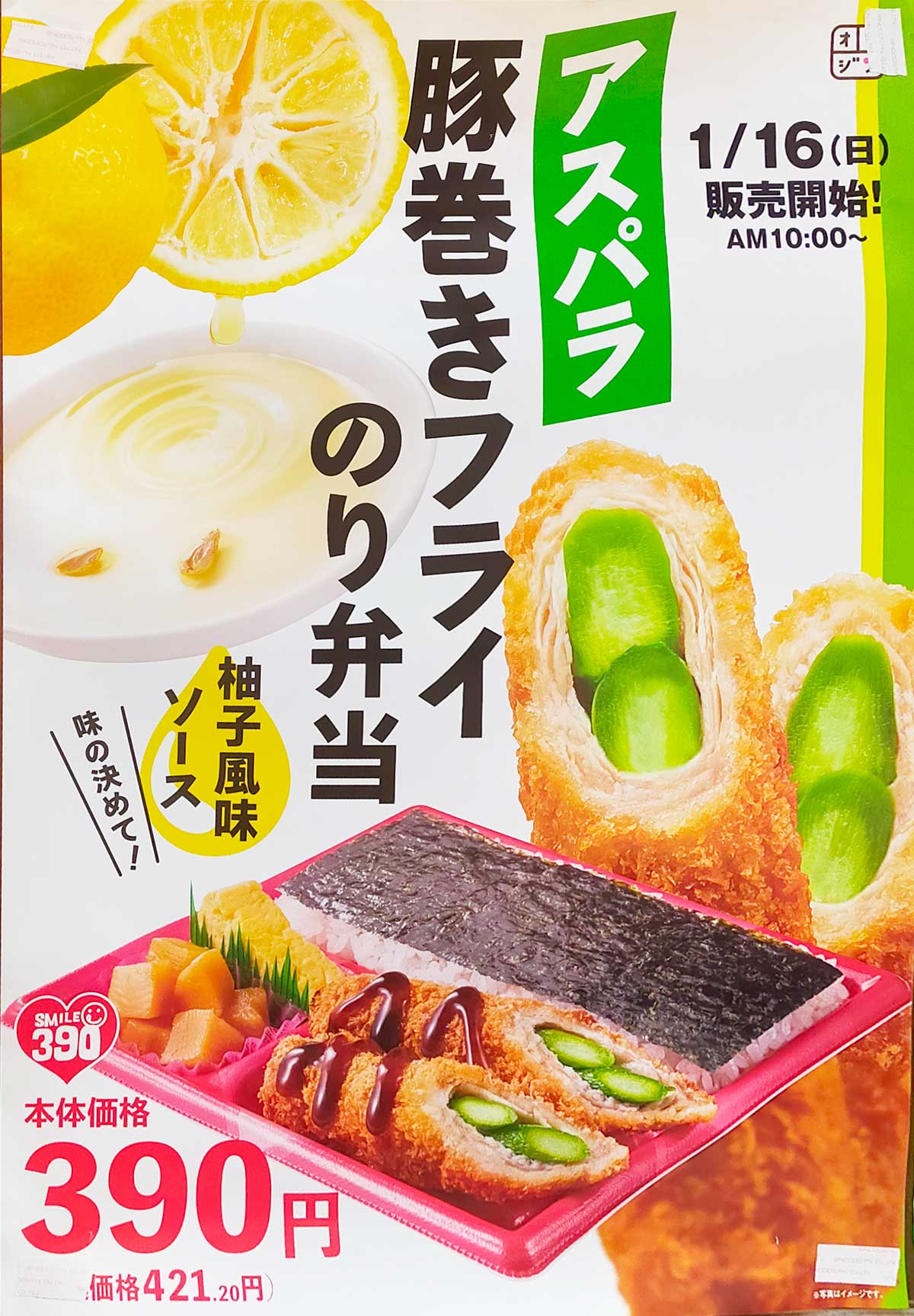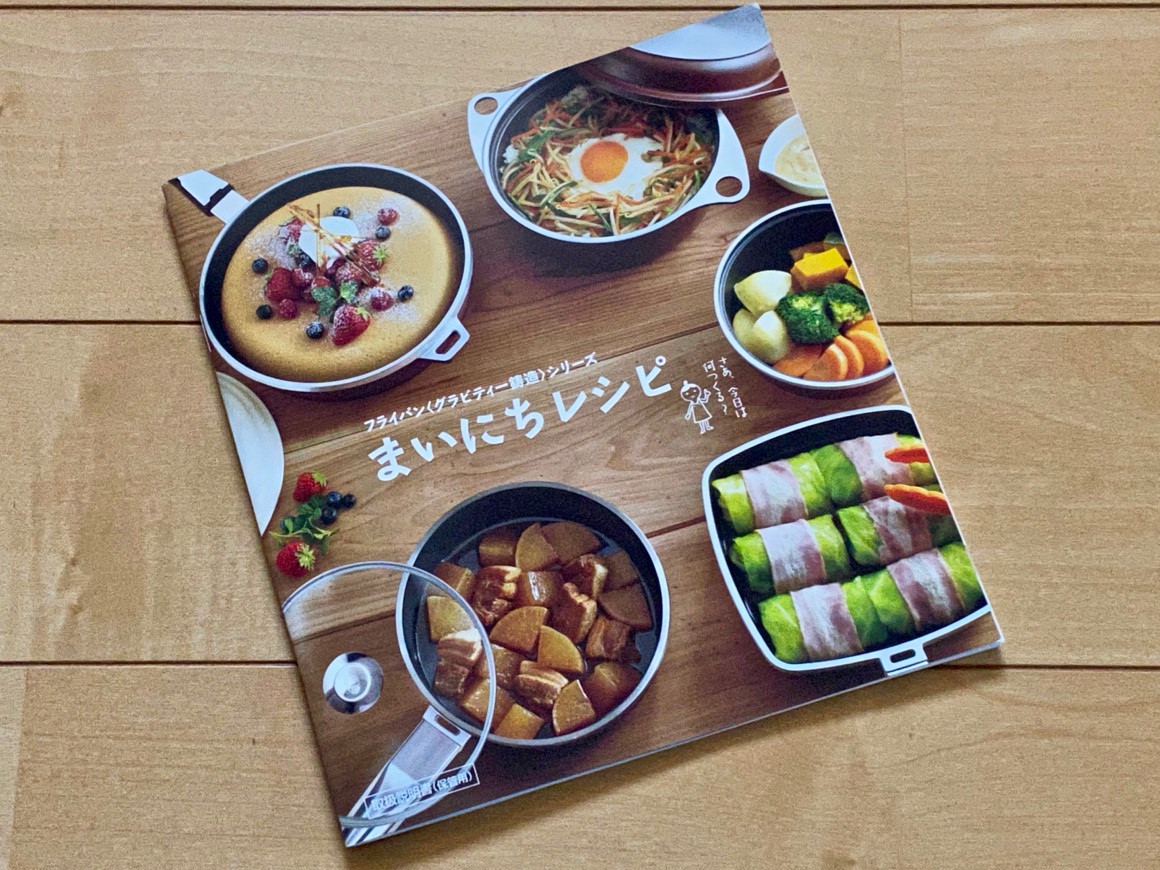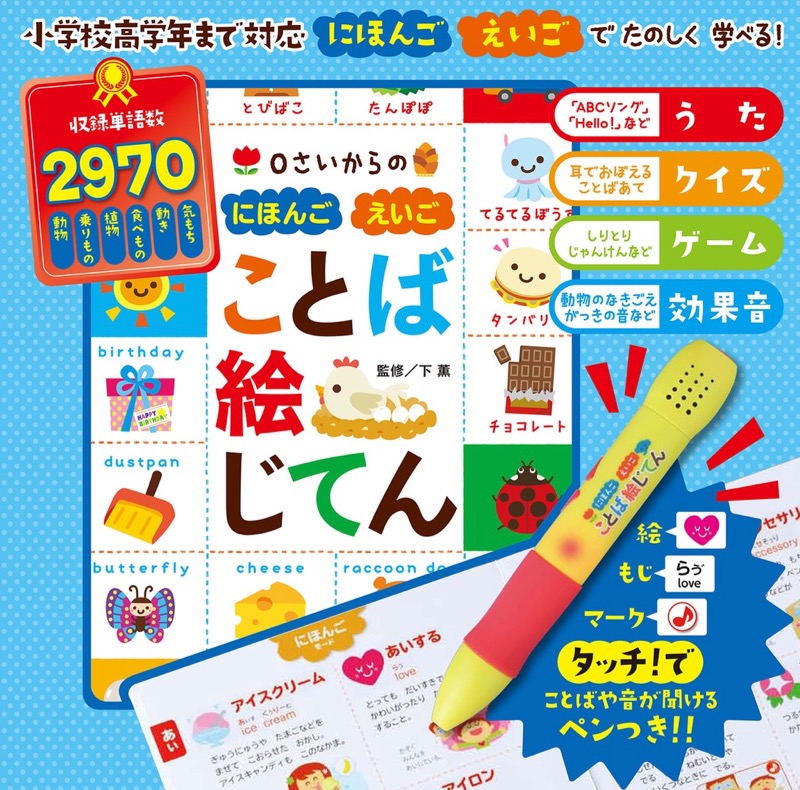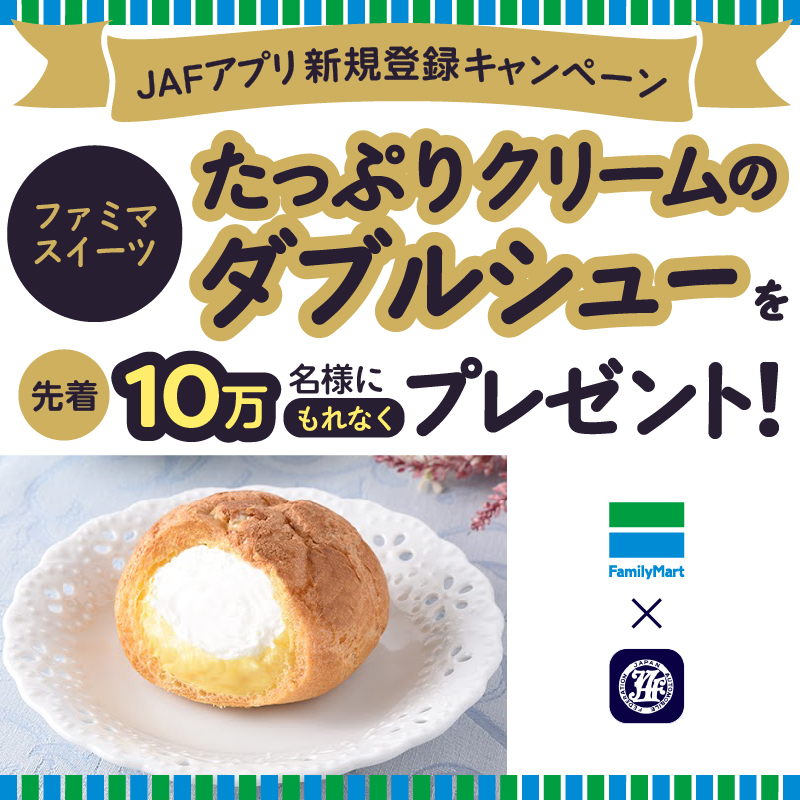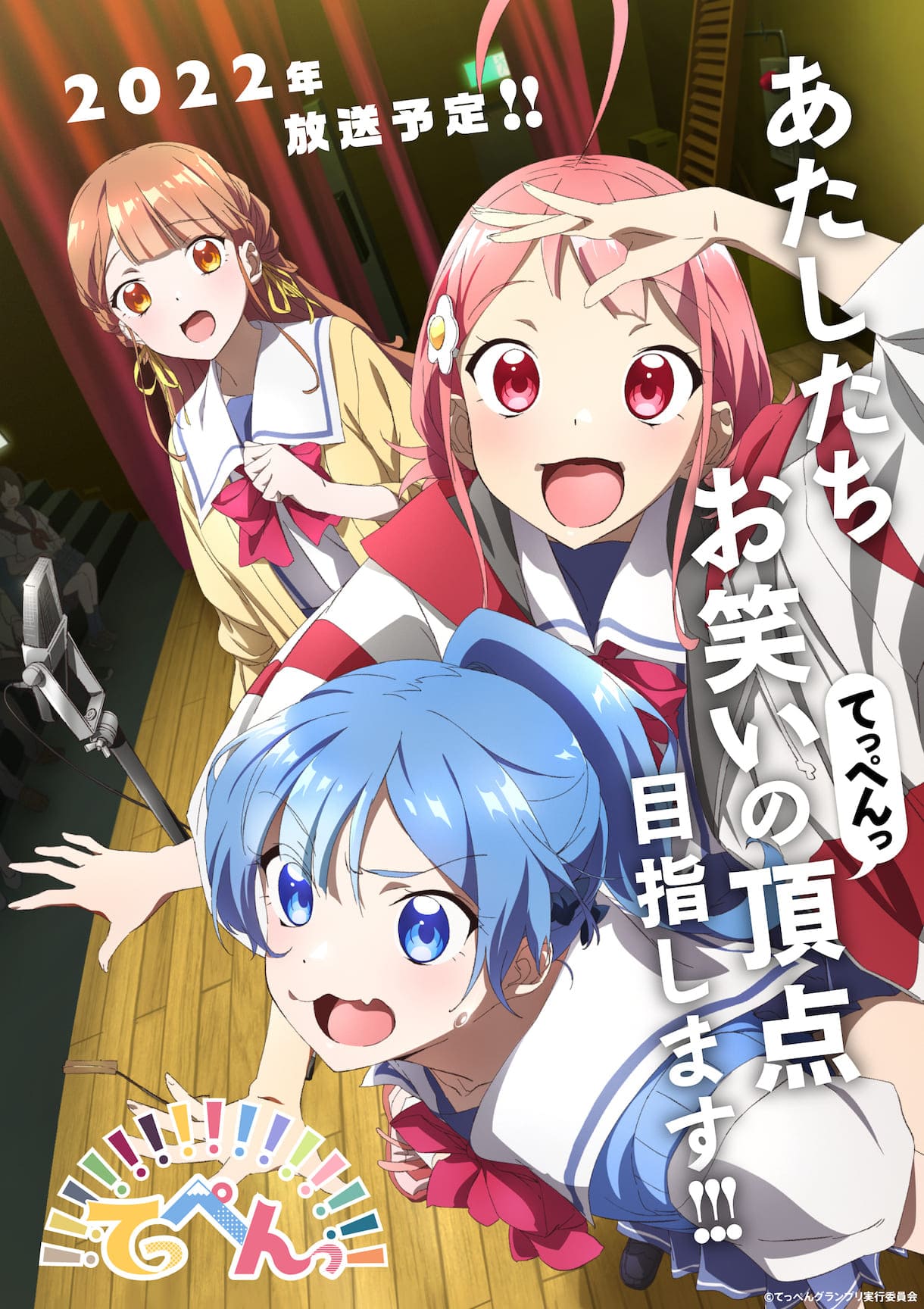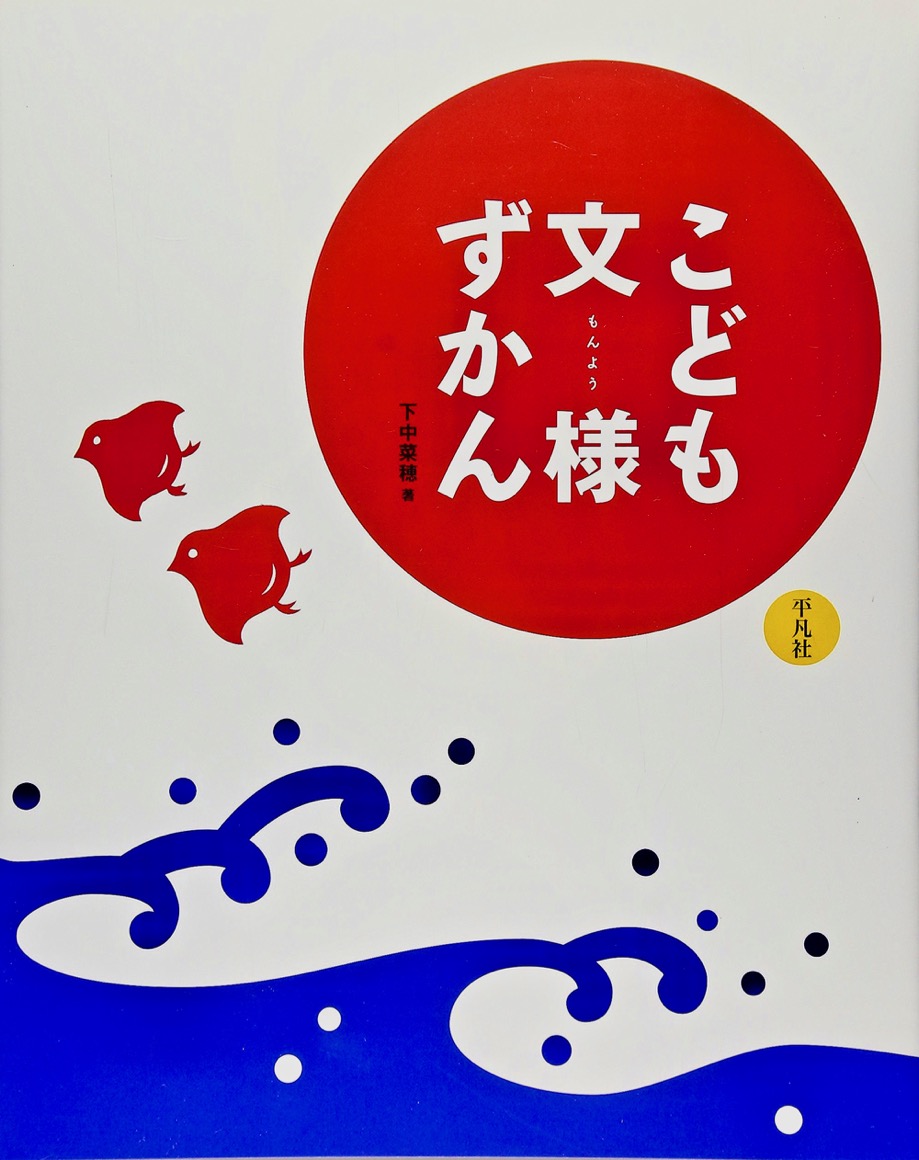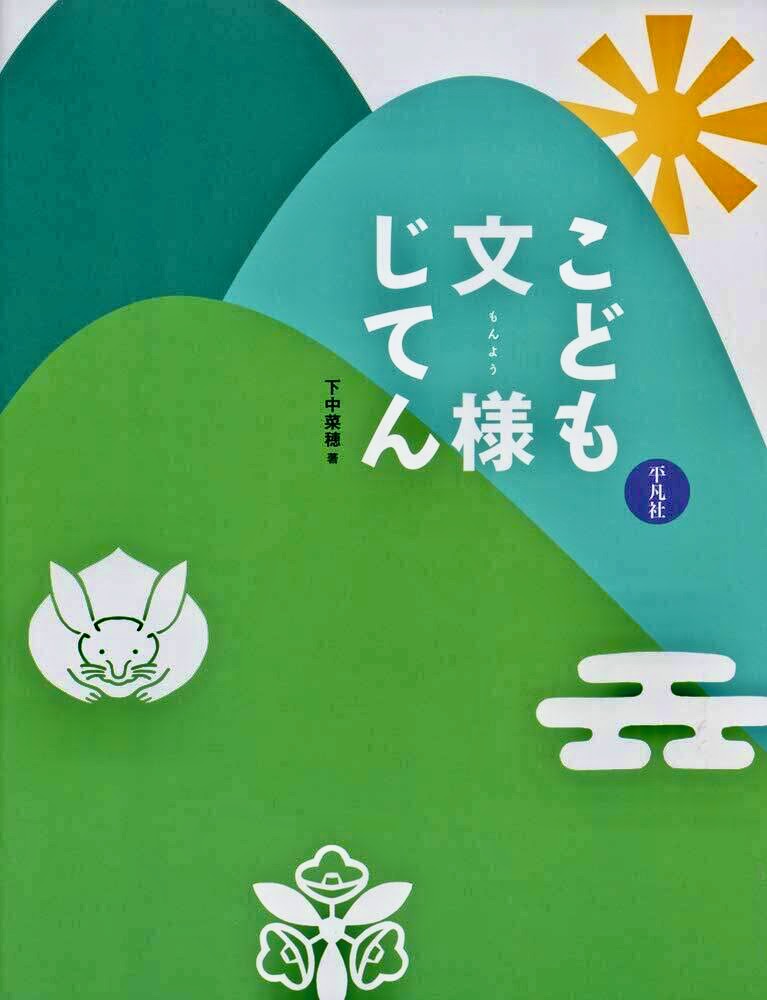
ミツカン酢のサイト。
これも…。
参天製薬公式サイト内の「目の情報ポータル」で「墨東レラ」を使った画像がちょこちょこ見られます。
男女のイラストの左右にある吹き出しの文字ですね。
「進行すると〜セルフチェック!」のところですね。
「墨東レラ」地味ではありますが、読みやすく、情報をしっかり伝えられる書体だと思います。
書名;のんちゃんのよっつのきせつ
原作:野末 信子
絵 :森島いずみ、森島つき
発行:創森社
「ジ」の濁点のひとつが傾けられている…。
こういう小手先のイジりって、効果があるんだろうか…。
書名:クワトロ・フォルマッジ
著者:青柳碧人
発行:光文社
東京都主税局の宣伝。
NHKの「今夜も生でさだまさし」。
「リユース&買取のサカイ」のCMです。
テロップに「墨東レラ」が使われています。
最後にこれも。
読みやすく、言葉が素直に届く気がしますね。
テレビ神奈川「超特急と行く!食べ鉄の旅」。
もうひとつ。
書名:聴く絵本むかしばなしベスト100
著者:でじじ
発行:パンローリング
同じシリーズ。
書名:せかいむかしばなしベスト100
著者:でじじ
発行:パンローリング
書名:ベルリン1919 赤い水兵 上
著者:クラウス・コルドン/酒寄進一
発行:岩波書店
書名:ベルリン1933 壁を背にして 下
著者:クラウス・コルドン/酒寄進一
発行:岩波書店
書名:ベルリン1945 はじめての春 下
著者:クラウス・コルドン/酒寄進一
発行:岩波書店
これは広告用画像かな…。